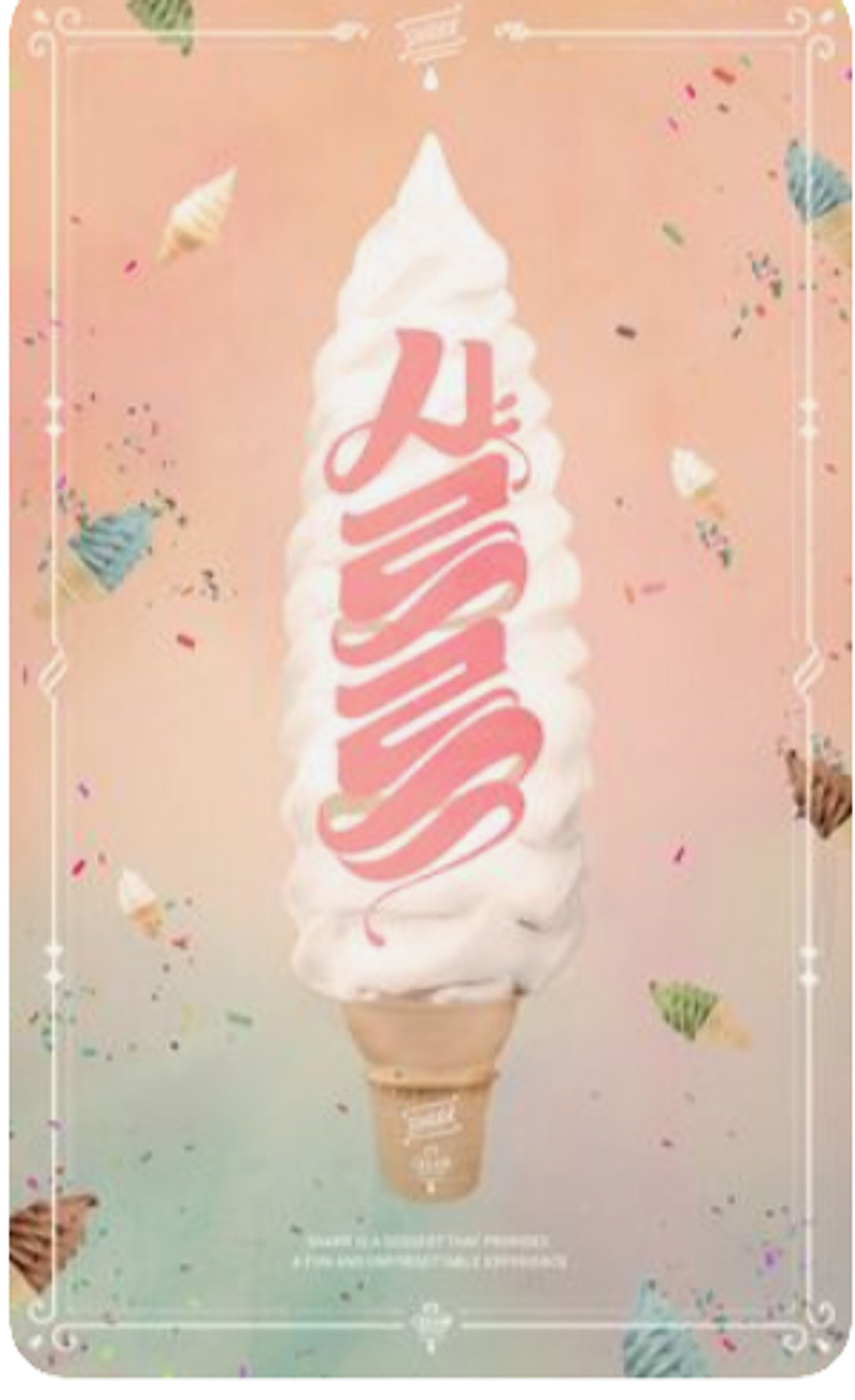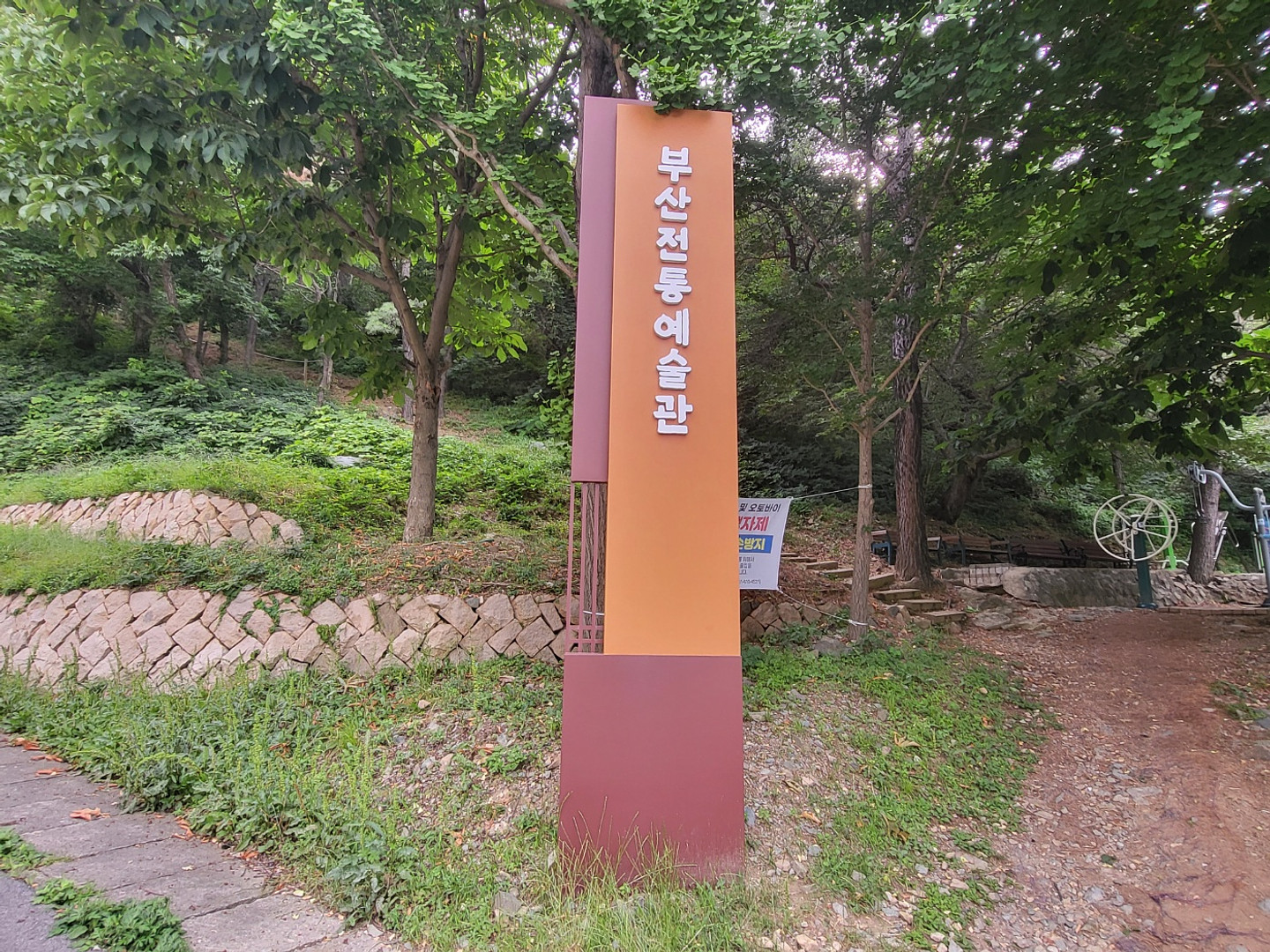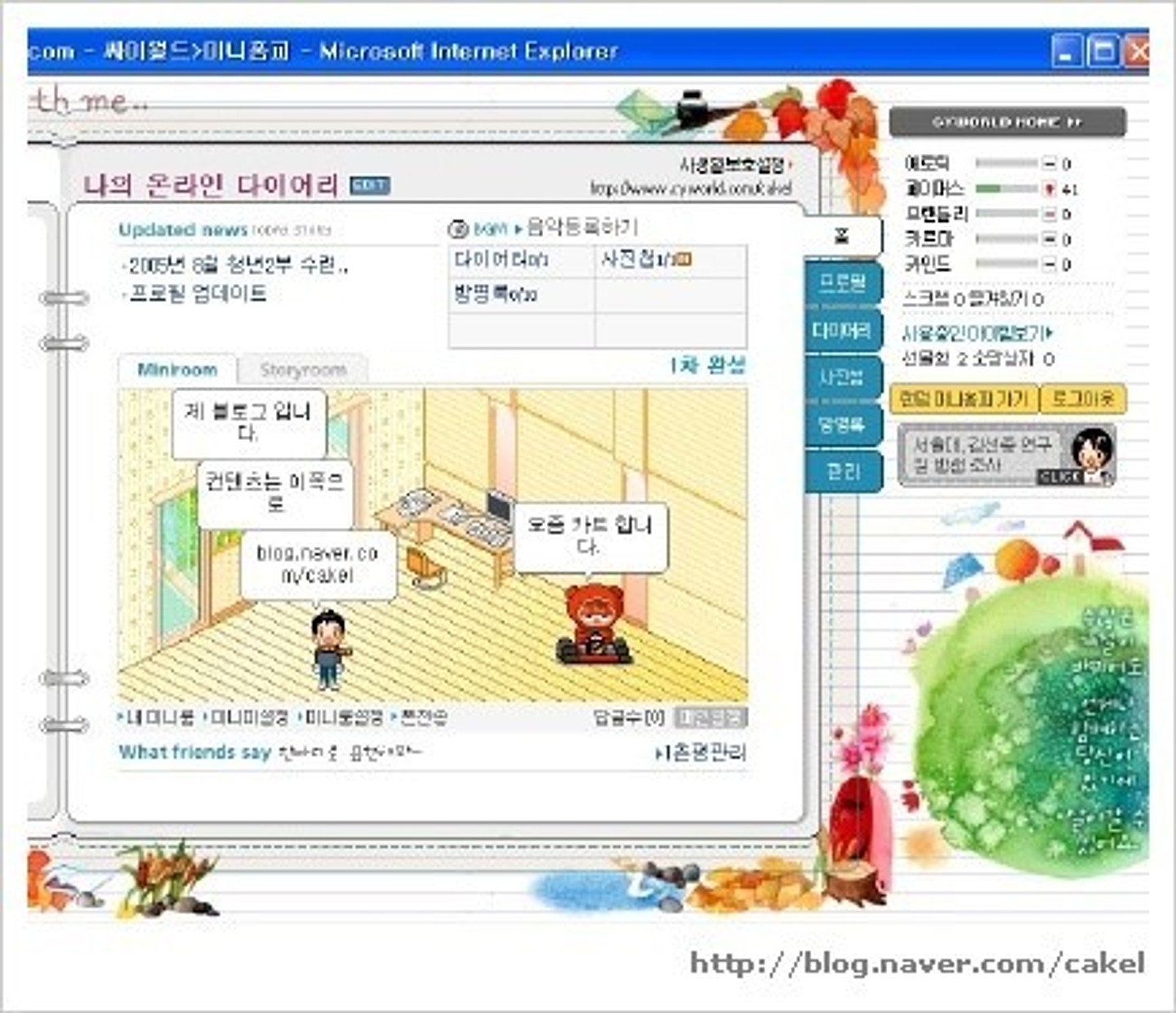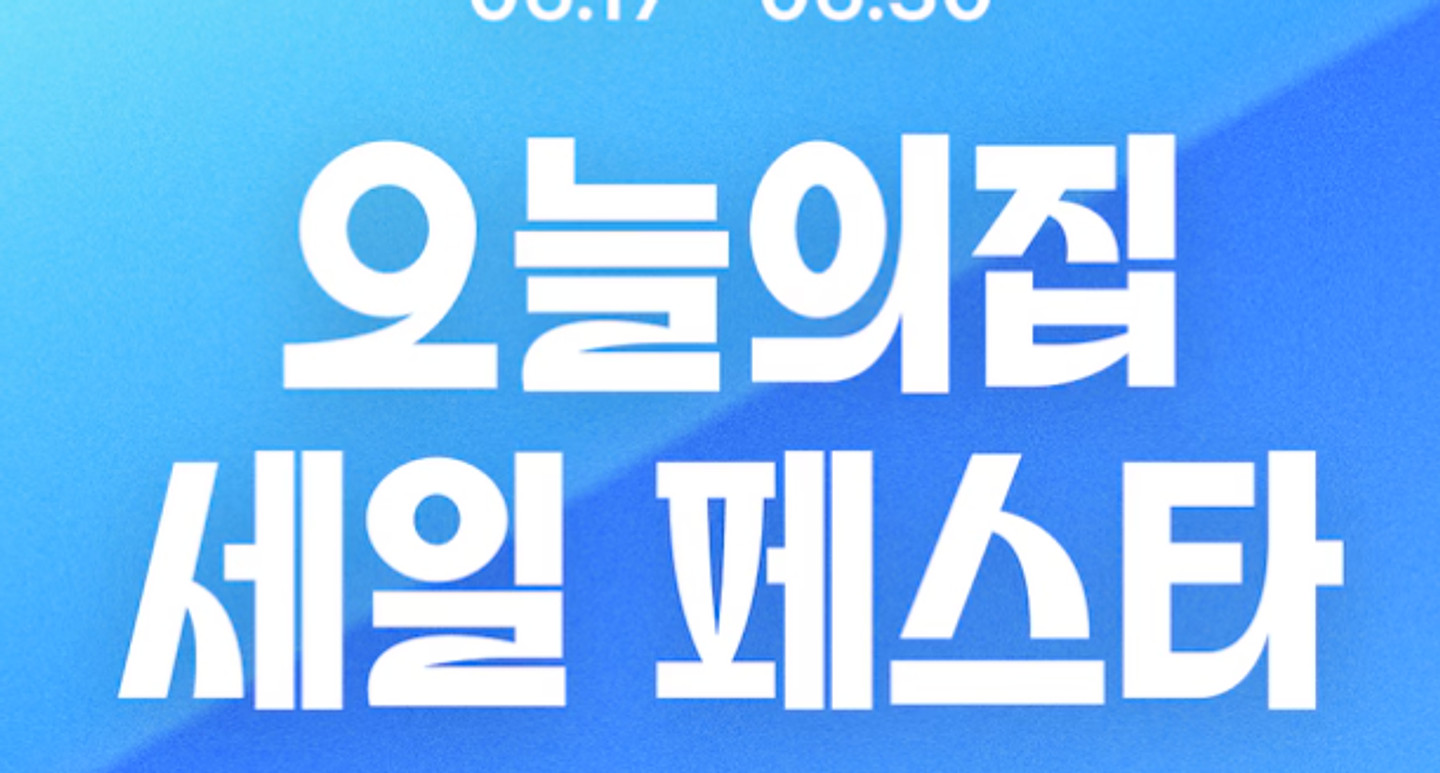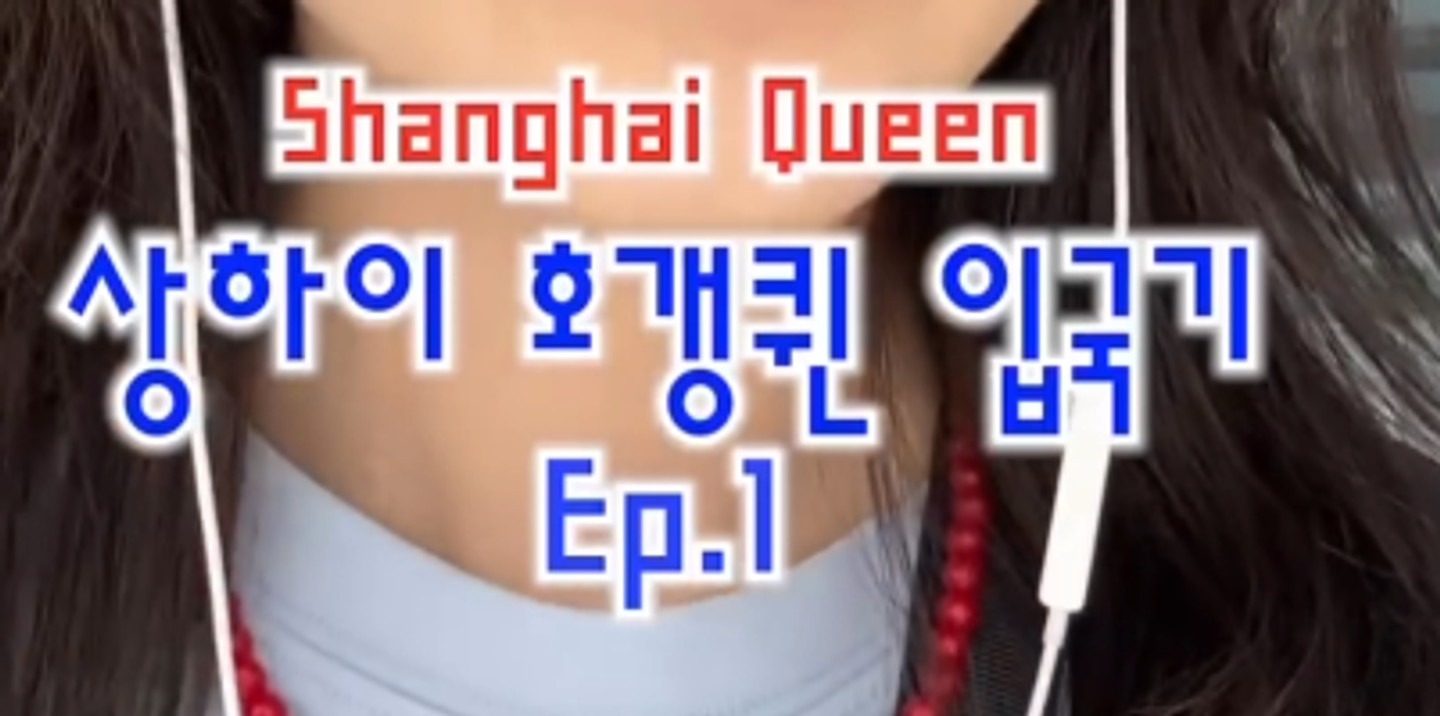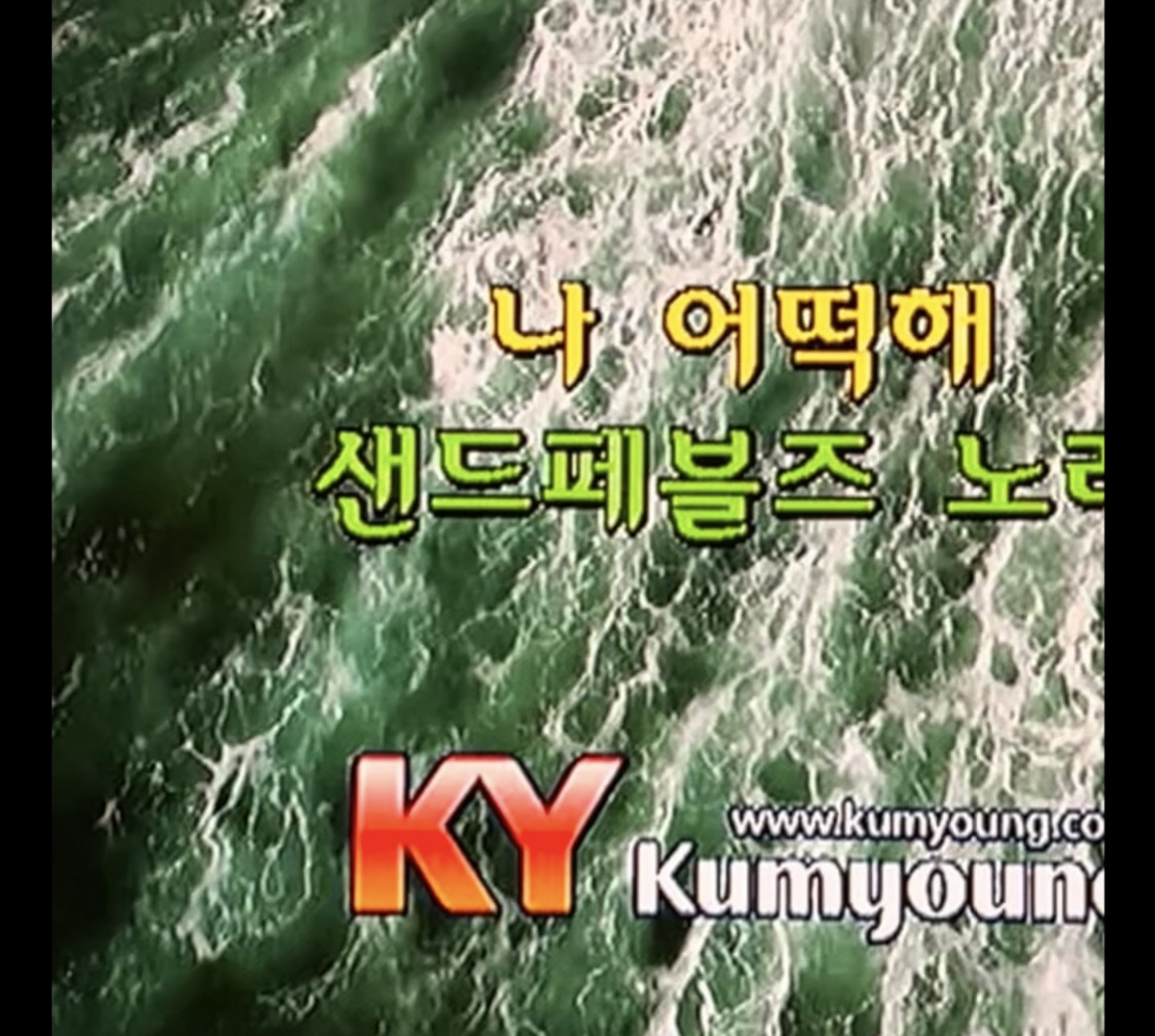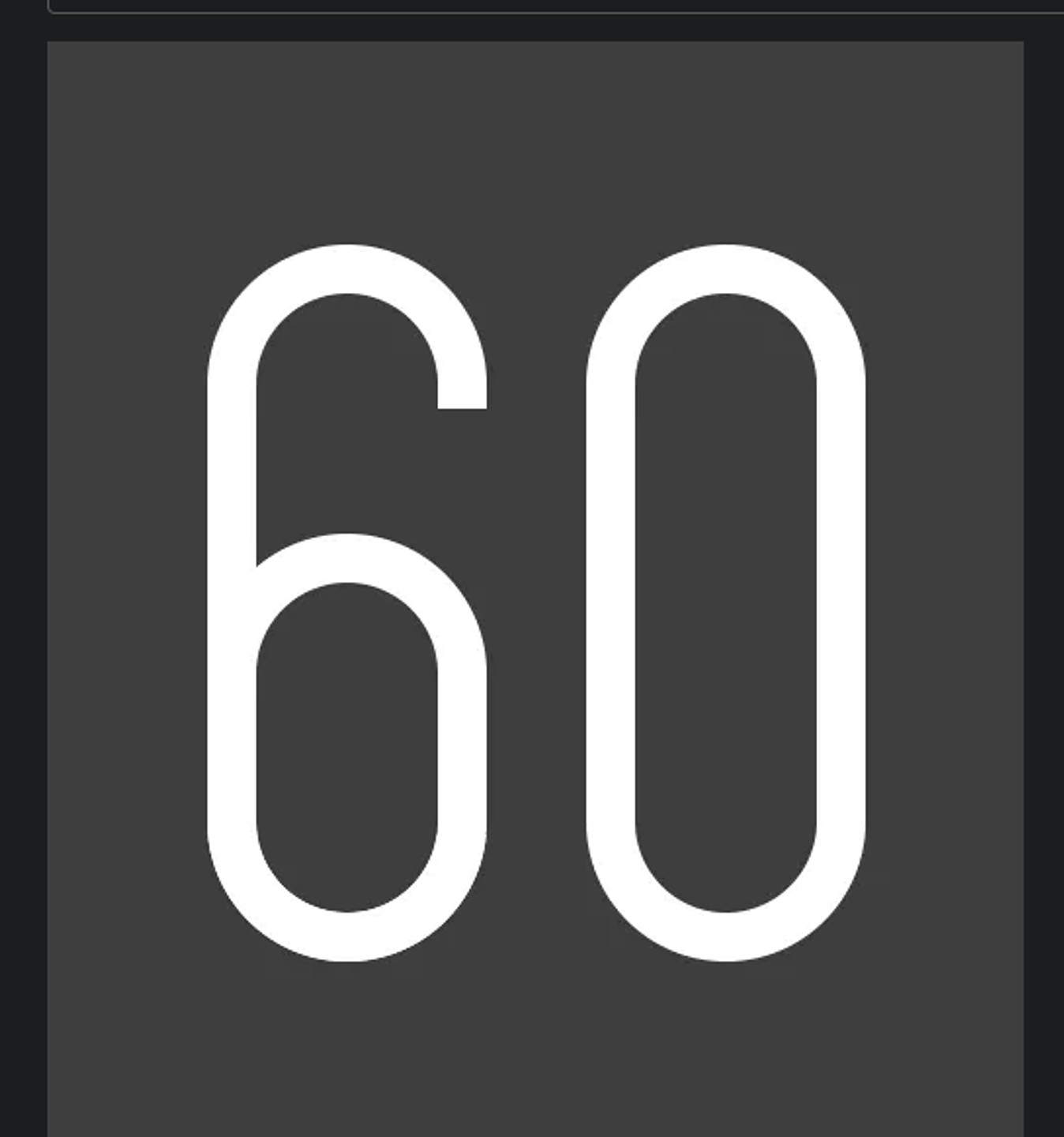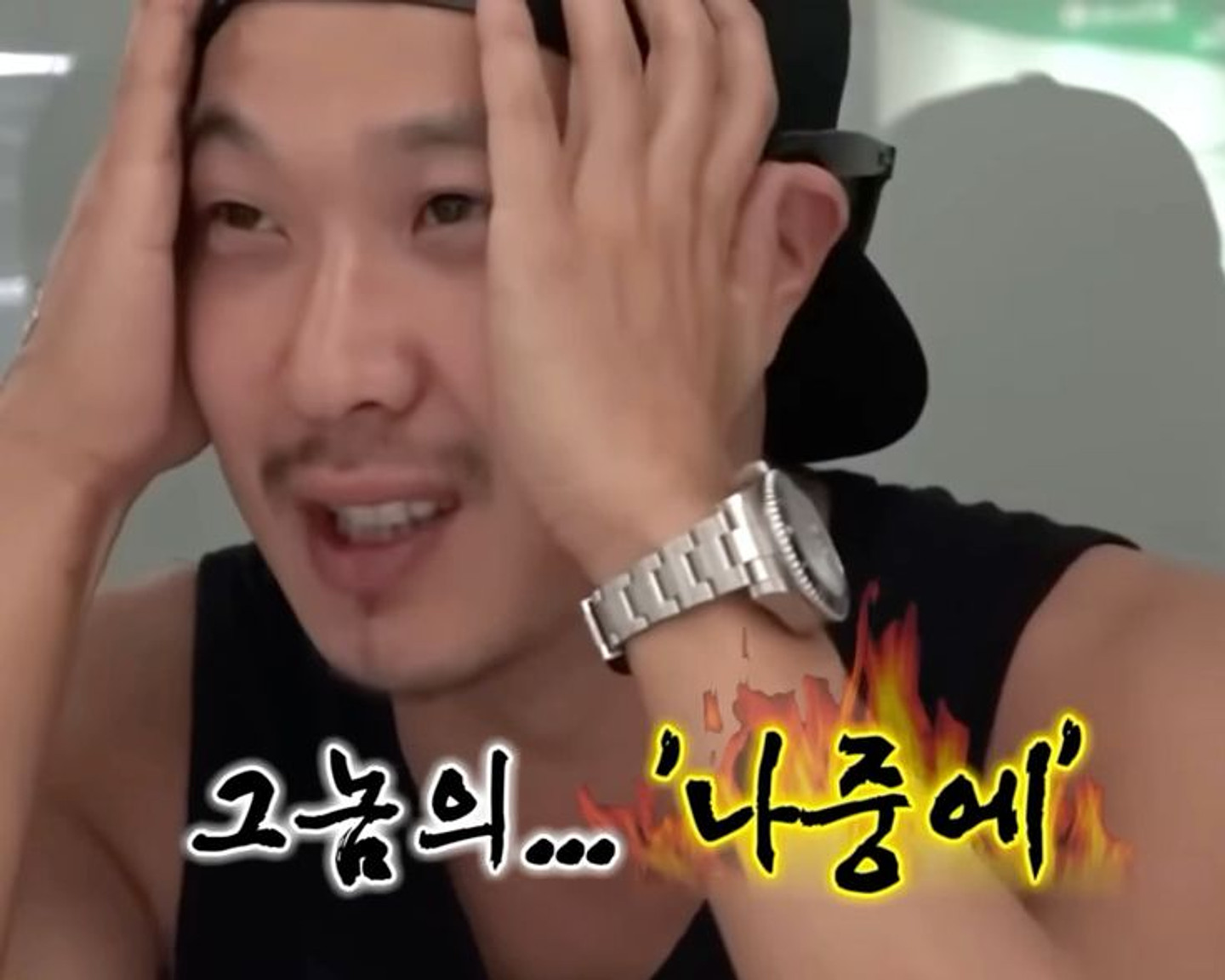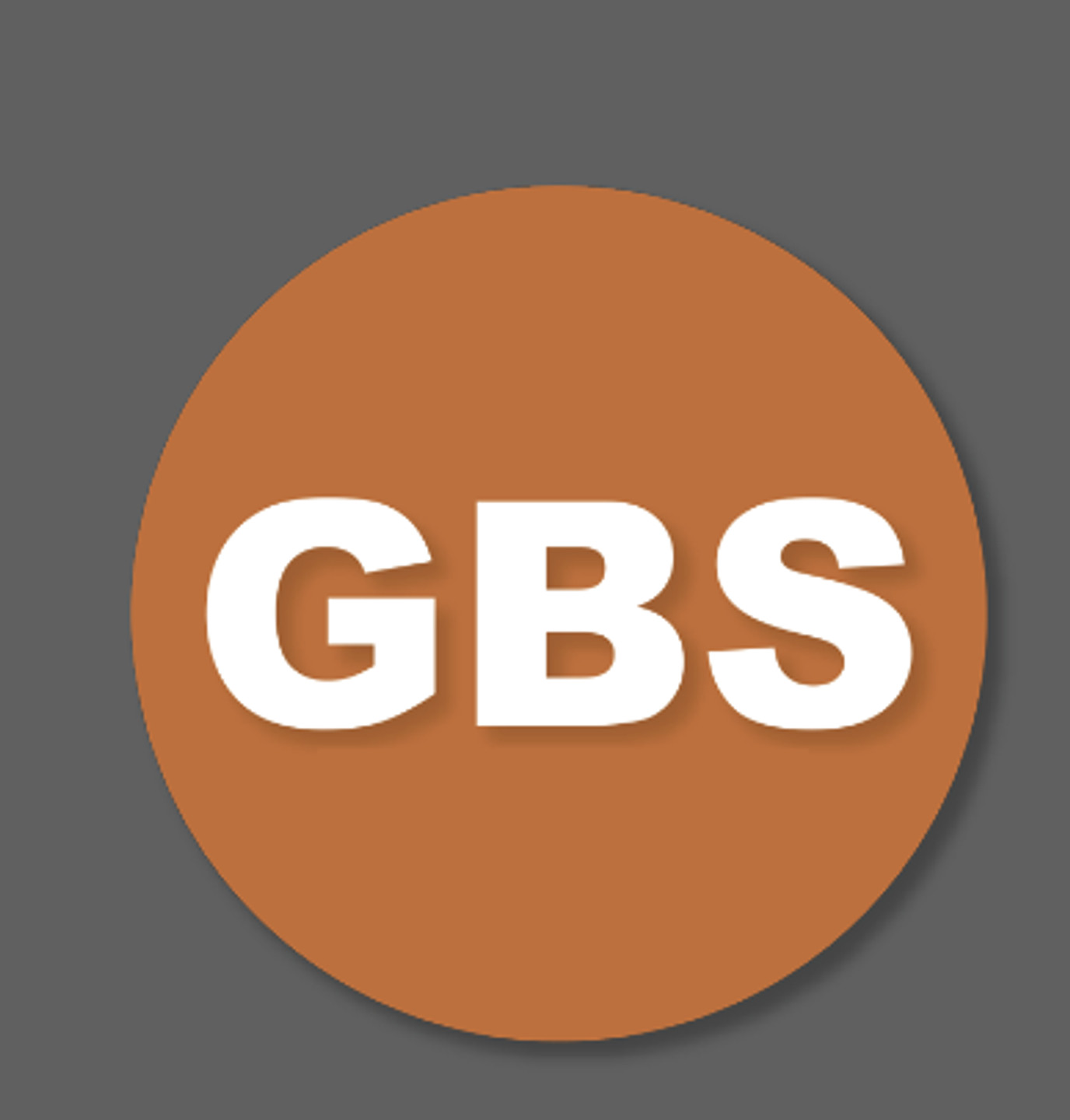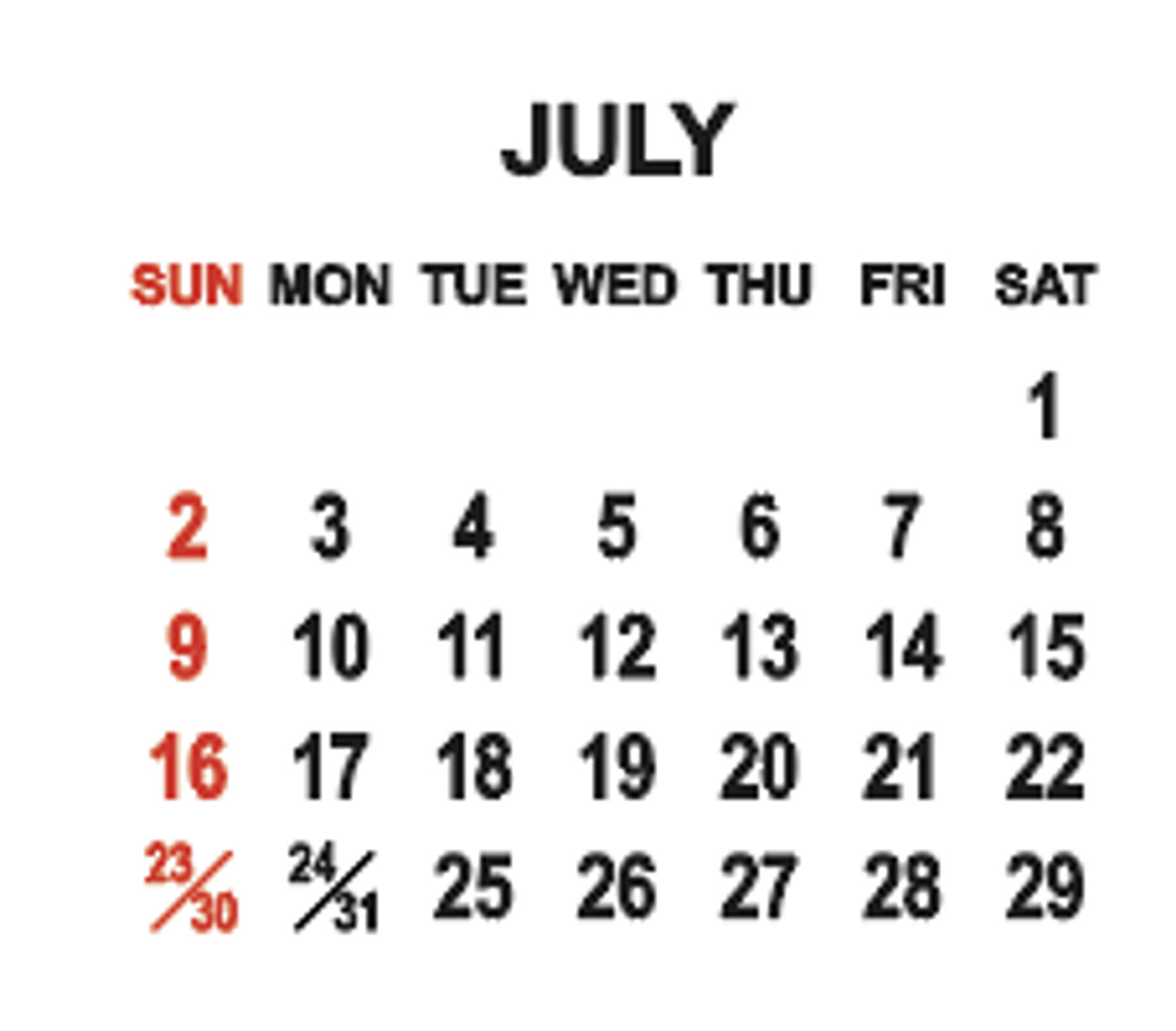
혹시 이 폰트 뭔지 아시나요 ㅠㅠㅠㅠ 꼭 알려주시면 감사하겠습니다 ㅠㅠ
혹시 이 폰트 무엇인지 아시나요? ㅠㅠ
이 폰트 무슨 폰트일까요?
화면에 사용된 폰트가 무엇인지 궁금합니다!
제발 알려주새요 이거뭔지 궁금해요….
무슨 폰트일까요??저런시옷은 없는거같아서 여쭤봅니다~
무슨 글씨체인가용
유투브 자막인데 무슨 폰트일까요?
유튜버 지냐님이 자주 사용하시는 폰트인데 뭘까요…? 나눔명조치곤 둥근거같고 볼드한느낌의명조체 궁금흡니다..
릴스에서 본 영어폰트가 알고싶습니다!
무슨 폰트인지 아시는 분 계실까요? 옛날 책에서 많이 본 것 같은데..
여기 쓰인 폰트가 궁금합니다.
친하지 않은 분 카톡프사에 적용되어있었는데 물어볼 자신이 없어서 여기에 여쭤봅니다 고수님들 알려주세요ㅠㅠ
이거 무슨 폰트인가용?
이거 무슨 폰트인가용??
몬스타엑스 자컨에서 IM(창균) 브이로그에 쓰인 폰트인데 어떤 폰트일까요?
이 폰트는 무엇인가요?
이 폰트 알려주시면 감사하겠습니다 새해 복 많이 받으세요
나라는 가수 자막 폰트 뭔가요!
나라는 가수 자막 폰트 뭘까요!
이 폰트 아시는 분 알려주세요ㅠㅠ
이폰트 뭔지 알 수 있을까요?
이 글씨체 모얌? 넷플릭스 글씨체인디
궁금해요!!
좋아하는 브이로거에 나온 폰트인데 이 폰트 어떤 폰트일까요..?ㅠㅠ
이 폰트 이름이 궁금합니다
이 폰트 무엇인가요? 오징어게임 투표할때도 나왔습니다.
이 폰트 무엇인지 아시는 분 잇나요!
식당을 인수 받고 셀프 작업 하려는데요 해당 사용된 폰트와 비슷한게 있을까요~? : )
소올님 유튜브에 나온 폰트가 궁금합니다 !
이거 무슨폰트일까요?
이 영어체가 뭘까요..?.?
폰트 명 궁금합니다
강민경님 송혜교 브이로그에 나온 폰트가 궁금합니다 !
티웨이날다체랑 느낌이 좀 다른 것 같은데 이 폰트 이름 뭔가요?
폰트 이름을 알고싶습니다! 알려주시면 감사하겠습니다(꾸벅)
이름 알려주시면 감사하겠습니다
이 폰트를 알고 싶습니다
글씨체 이름 알려주시면 감사하겠습니다
이 폰트 이름 알려주시면 감사하겠습니다!!
'청춘의 포말' 이랑 'YOUTH' 폰트 뭔가요? 만약에 다르다면 각각 알려주세요!
영문폰트알고싶어요.
영문,한글폰트이름알고싶어요.
폰트너무알고싶어요!!
폰트이름알고싶어요.
이 폰트 무엇인지 아시는 분 있나요?
고운돋움이랑은 조금 다른 것 같은데 ㅠㅠ 폰트 정보 부탁드립니다!
이거 폰트 뭔지 아시는분 ㅠㅠ
이거 폰트 뭘까요? 넘 궁금해요 ㅠㅠ
뭐에요?
전에 쓰던 폰 폰트인데 폰 바꾸고 어떤 폰트인지 찾질 못하겠네요 도와주세요
제발 알려주세요
무슨 폰트인지 알까요? 산돌구름에 검색해봐도 안나오네욤 ㅠ
카카페가 사용하는 기본 고딕체가 어떤 고딕체인지 알고 싶어요
이 폰트 뭔지 아시는 분 계실까요??
폰트 정보 부탁드립니다 ㅜㅜㅜㅜ!!
이 폰트 뭔지 알고싶습니당!
폰트 정보 궁금합니다..!